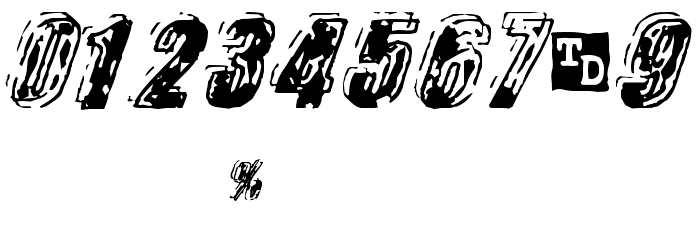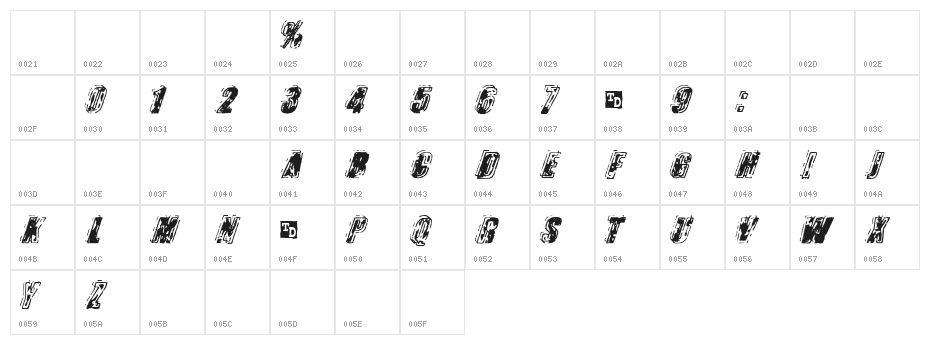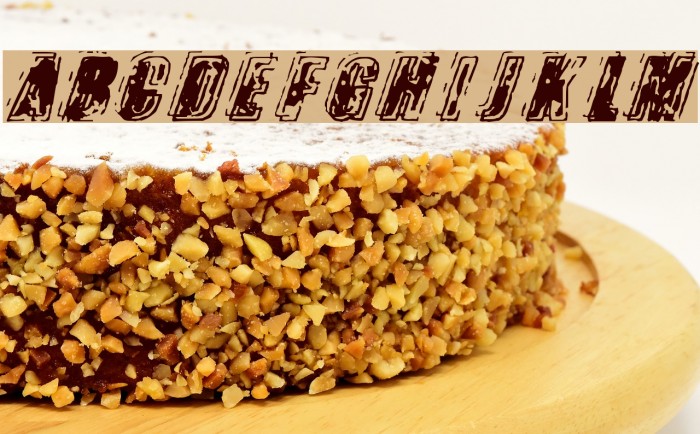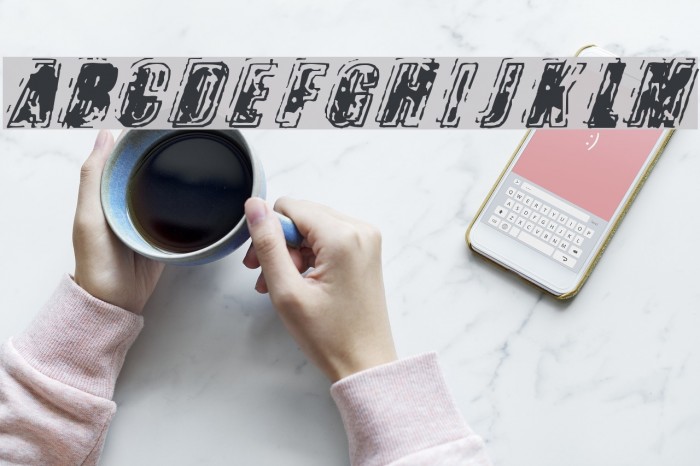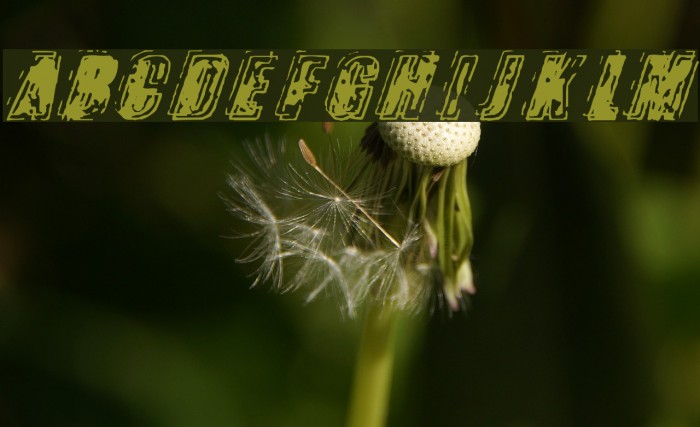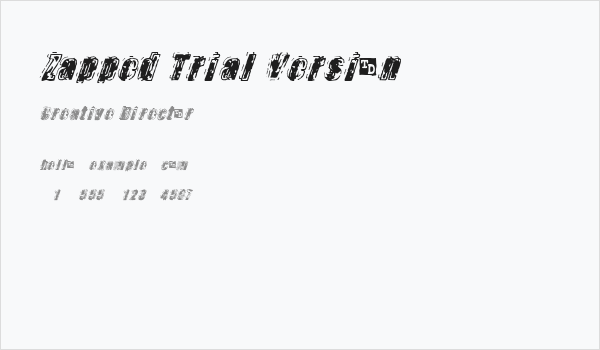
Zapped Trial Version Font
| Vorgeschlagene Projekte | Ideal for posters, album covers, event flyers, and any project needing a bold, eye-catching design. |